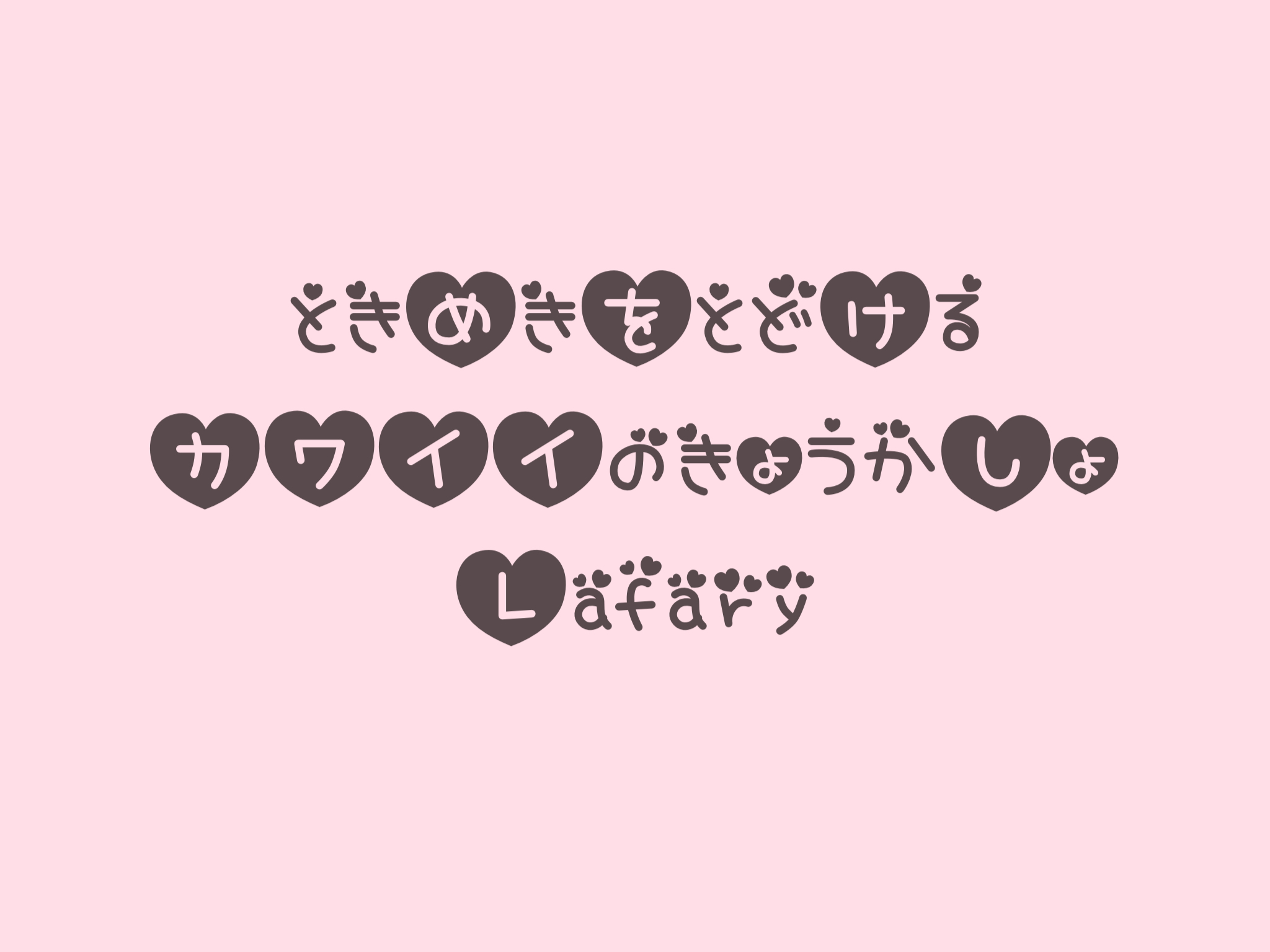
ジャニヲタ フォント 日本語
ジャニヲタ インスタ ストーリー 量産型 量産型ヲタク 量産型 フォント 日本語フォント 写真の4番目のフォントのお名前を教えていただきたいですどなたか知っている方教えて下さい!.
ジャニヲタ フォント 日本語. 「ジャニヲタさんがよく使っているこのフォントって何? ってフォントがここで見つかるよう、今回はジャニオタさんがうちわやタグ画によく使っている ハートのデザインのフォント をまとめてみようと思います。. ジャニヲタさんがよく使っているこちらのフォントを探して Heroes of Dragon Age (@HeroesofDA) Twitter ポケモンGOシンオウの石で進化させるべきはドサイドン チキンマカロニグラタン E・レシピ料理のプロが作る簡単. フォントを指定できるのは英数字のみです。 小文字や数字が使えないフォントもあります。 URLやハッシュタグにフォントを付るとTwitterでリンクにならない場合があります。 当サイトは趣味で運営されています。.
フォントフリーについて font free(フォントフリー)は、無料で使える日本語フリーフォント投稿サイトです。 漢字やカタカナ、ひらがなをはじめとした日本語の無料フォントを、明朝やゴシック、手書きなどのカテゴリーから探すことができます。. ジャニヲタ必見の可愛すぎるフォント特集! フォントとは、字体のことです。 このフォント次第で、文字の印象が変わります。 コンサートの応援グッズなどには、他の人より可愛く、目立つグッズにするためにいろんなフォントが使われています。. ジャニヲタさんが使う可愛いフォントは ジャニヲタさんが使うフォントを見て、「うわぁこのフォント私も使いたい」と思ったことありませんか? 可愛いと思うフォントや見やすくて人気のフォントは以下の 4 つではないかと思います。.
ジャニーズファンであれば、ライブに行く時に必須の手作りうちわ。 ライブでは多くのファンが手作りうちわで参戦しています。 しかし、どうやったら上手に作れるのかわからなく悩んでいる人も多いでしょう。 今回は、ジャニーズうちわの上手な作り方や、実際にいろいろな人が作っている. 昭和レトロでかわいいひらがなフォント 収録文字:ひらがな 商用利用可能 LINEスタンプ使用可能 ダウンロード. 17年4月28日 しょうわのにをい 日本語フォント 17年4月28日 ほそふわフォント.
まきばフォント ひらがな、カタカナ、漢字 ので遠くからも見やすく、目立ちやすいフォントなのではないでしょうか。 ちょっと斜めの文字がキュートな手書きフォント。 元気のよい表現にピッタリ合いそうです。 ななキュンのうた ひらがなを表示できるフリーフォントの一覧です。日本語. ジャニヲタ フォント 日本語 Font freeフォントフリーは無料で使える日本語フリーフォント投稿サイトです 漢字やカタカナひらがなをはじめとした日本語の無料フォントを明朝やゴシック手書きなどのカテゴリーから探すことができます紹介. ジャニヲタ愛用の可愛いフォントの名前と使う方法は?うちわ Windows 8 での Flash Player に関する問題 Bickham Script Font FontPalacecom Nexus 5 android 6 レザージャケット・ライダース着こなしコーデ!レディース.
ジャニヲタさんが使う可愛いフォントは ジャニヲタさんが使うフォントを見て、「うわぁこのフォント私も使いたい」と思ったことありませんか? 可愛いと思うフォントや見やすくて人気のフォントは以下の 4 つではないかと思います。.